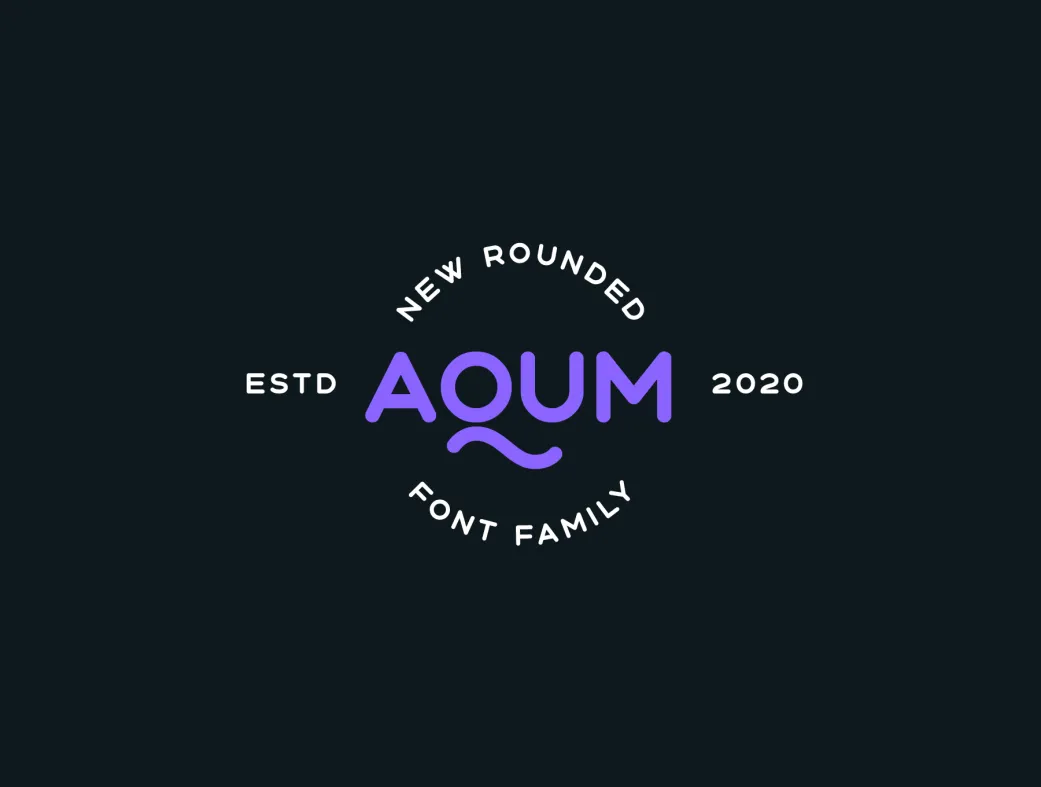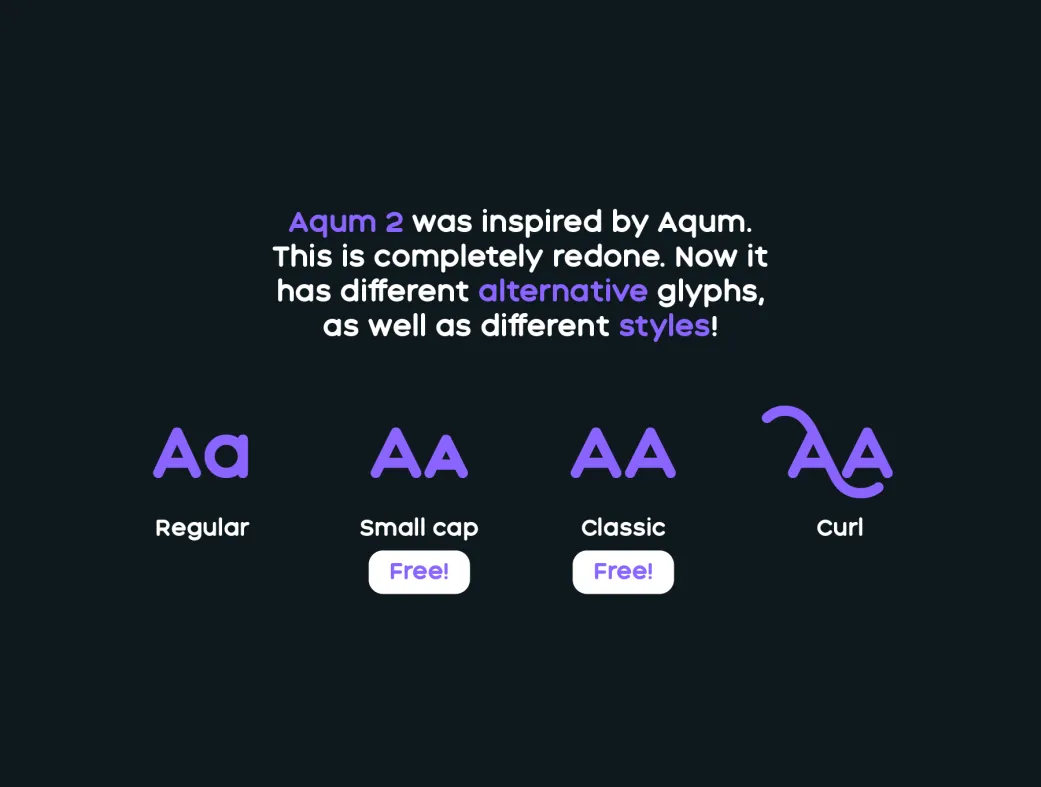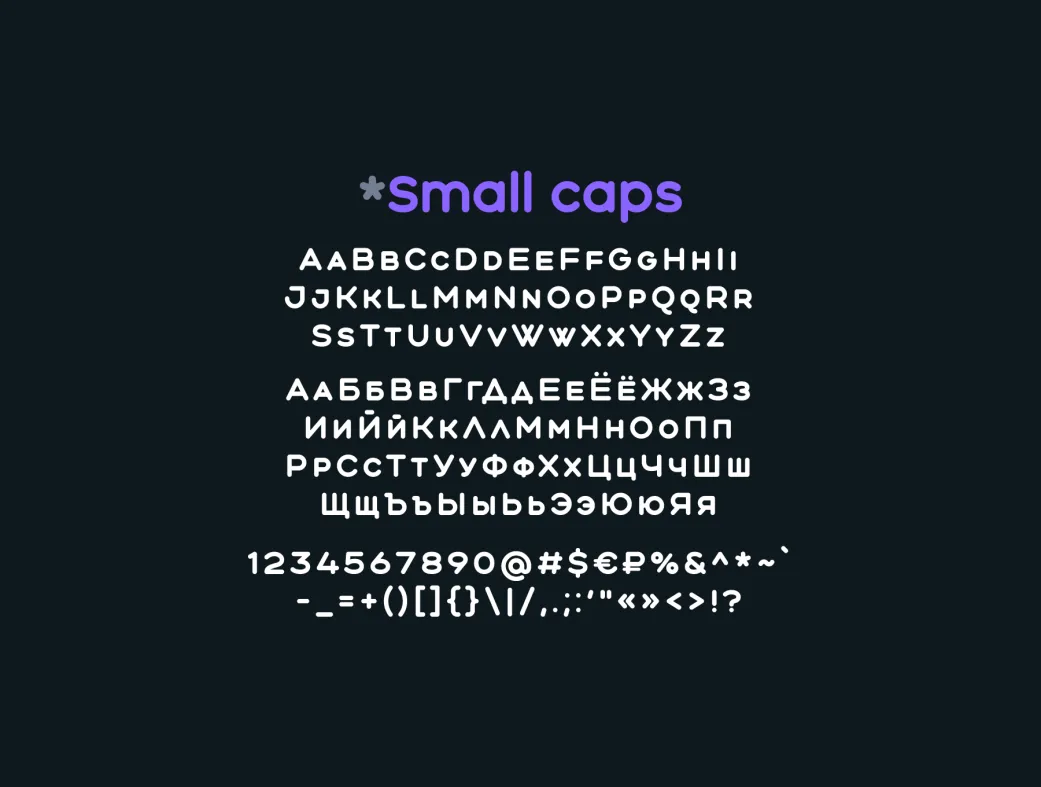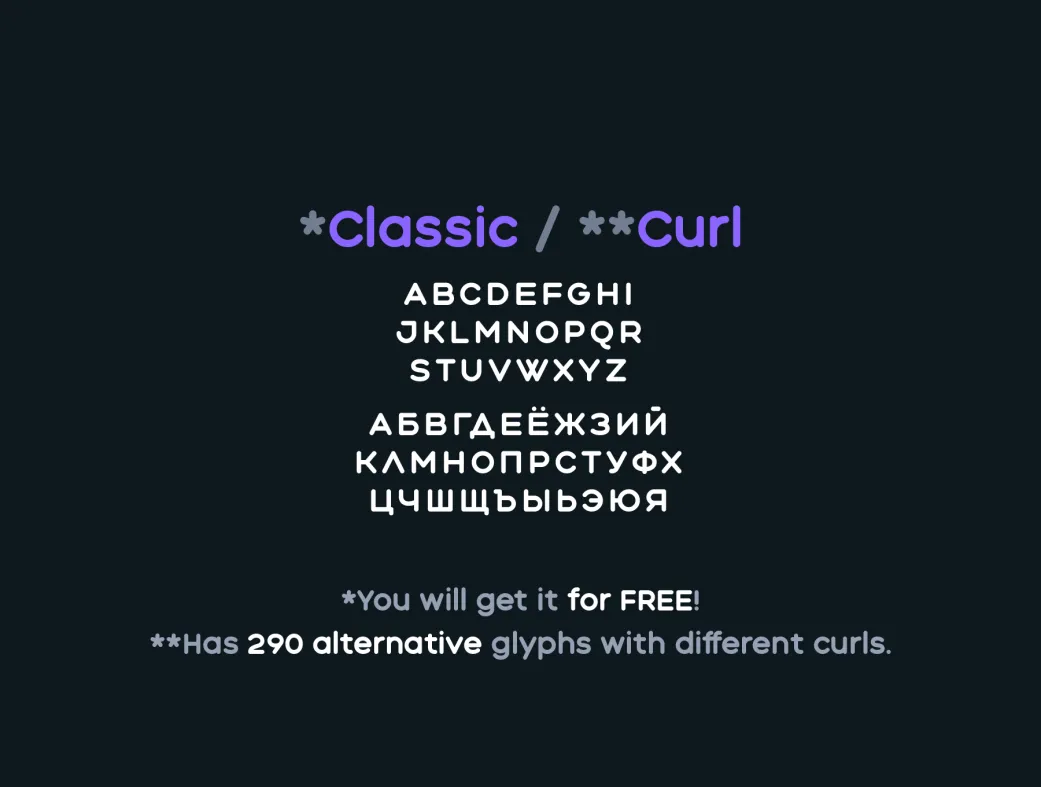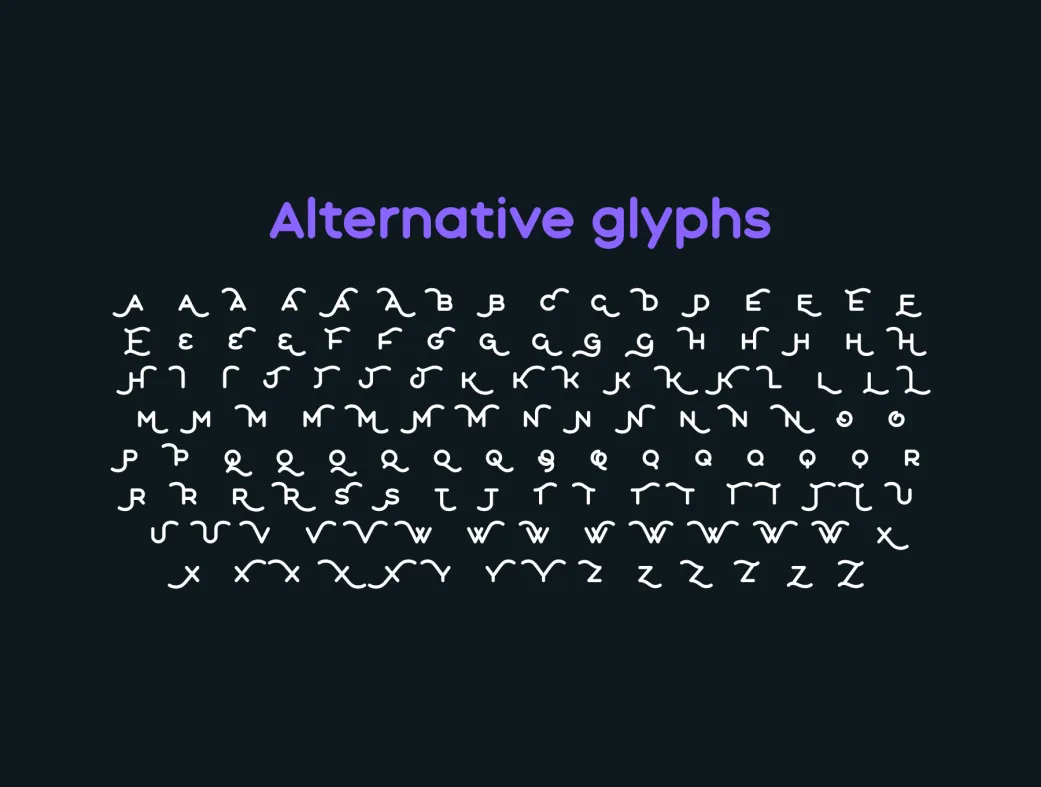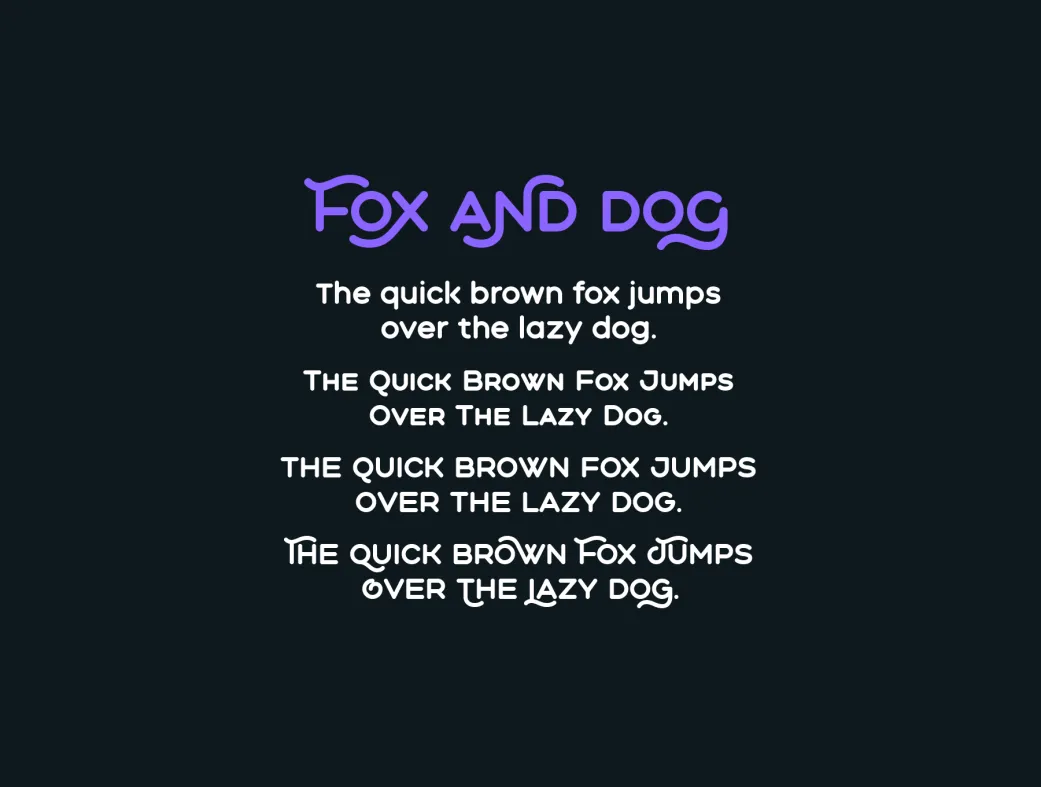
فونت فمیلی Aqum ۲
فونت گرد و مدرن Aqum 2 برای لوگوها، هدرها و چاپ‌های حرفه‌ای ایده‌آل است.
Aqum 2 - rounded font family
معرفی خانواده فونت گرد Aqum 2
خانواده فونت گرد Aqum 2 یک مجموعه نوآورانه و مدرن از فونت‌های sans serif است که با طراحی هندسی و گرد، ظاهری تازه و جذاب به پروژه‌های طراحی شما می‌بخشد. این فونت با پشتیبانی از بیش از ۵۰ زبان، گزینه‌ای عالی برای طراحان ایرانی و بین‌المللی به شمار می‌رود که به دنبال دانلود فونت‌های باکیفیت و رایگان برای استفاده تجاری هستند.
ویژگی‌ها و مزایای فونت Aqum 2
فونت Aqum 2 شامل ۴ سبک متنوع است که یکی از آن‌ها به صورت رایگان (برای استفاده شخصی و تجاری) در دسترس قرار دارد. این فونت با حروف لاتین و سیریلیک، برای ایجاد لوگوهای چشمگیر، هدرهای وب‌سایت و مواد چاپی مانند بروشورها و پوسترها ایده‌آل است. طراحی گرد و هندسی آن، خوانایی بالا را با ظاهری مدرن ترکیب می‌کند و به شما کمک می‌کند تا در جستجوهای گوگل برای "فونت sans serif مدرن" رتبه بهتری کسب کنید.
از Aqum 2 در طراحی لوگوهای برندینگ، تیترهای وب و اپلیکیشن‌ها استفاده کنید تا ظاهری نرم و دوستانه ایجاد شود. این فونت برای پروژه‌های دیجیتال و چاپی مناسب است و با ابزارهایی مانند Adobe Illustrator یا Figma سازگار می‌شود.